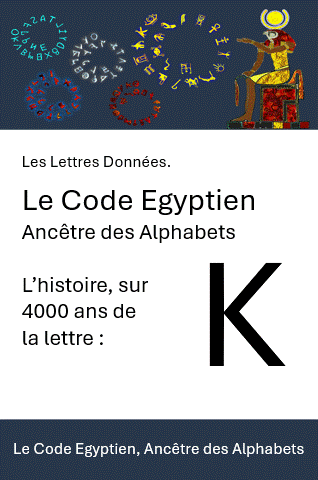
Haroëris, l’Horus aux deux yeux, est comme Rà un faucon aux ailes à demi déployées ou un homme à tête de faucon, les bras ouverts formant un angle.
L’un de ses identifiants est l’œil souligné de deux traits, une graphie qui sera célébrée pour Horus, les Égyptiens en faisant l’un de leurs signes mystiques les plus chargés de sens, y compris numérologique.
.En Proto-Cananéen la silhouette est épurée et présente les particularités qui en feront l’inspirateur de ce qui devient le Phénicien Kaph, symbole de la paume, ou de la main.
En Araméen le Kaph et en nabatéen, est aussi le symbole pour la paume. Comme pour nombre de transpositions depuis le Phénicien, si le sens parait conservé, le graphisme laisse perplexe même si l’on perçoit la ressemblance du haut de la lettre avec son inspirateur Phénicien.
Une tendance que l’on ne retrouve pas en Grec Archaïque, puisque le Kappa ancien devient le classique, soit une forme inchangée.
L’Étrusque transmet le « K-miroir » très similaire à celui du Phénicien, que les Latins inversent avant de le fixer en K définitif, suivant en cela l’exemple Grec.
Haroëris, figure de la justice combattante, est le guerrier dévoué à la cause du grand pays, à commencer par la protection de Rà. Il est inflexible, aussi bien envers ce qui provient de l’extérieur, que vis-à-vis des dangers intrafa-miliaux que concrétisent les fantaisies lugubres de Seth.